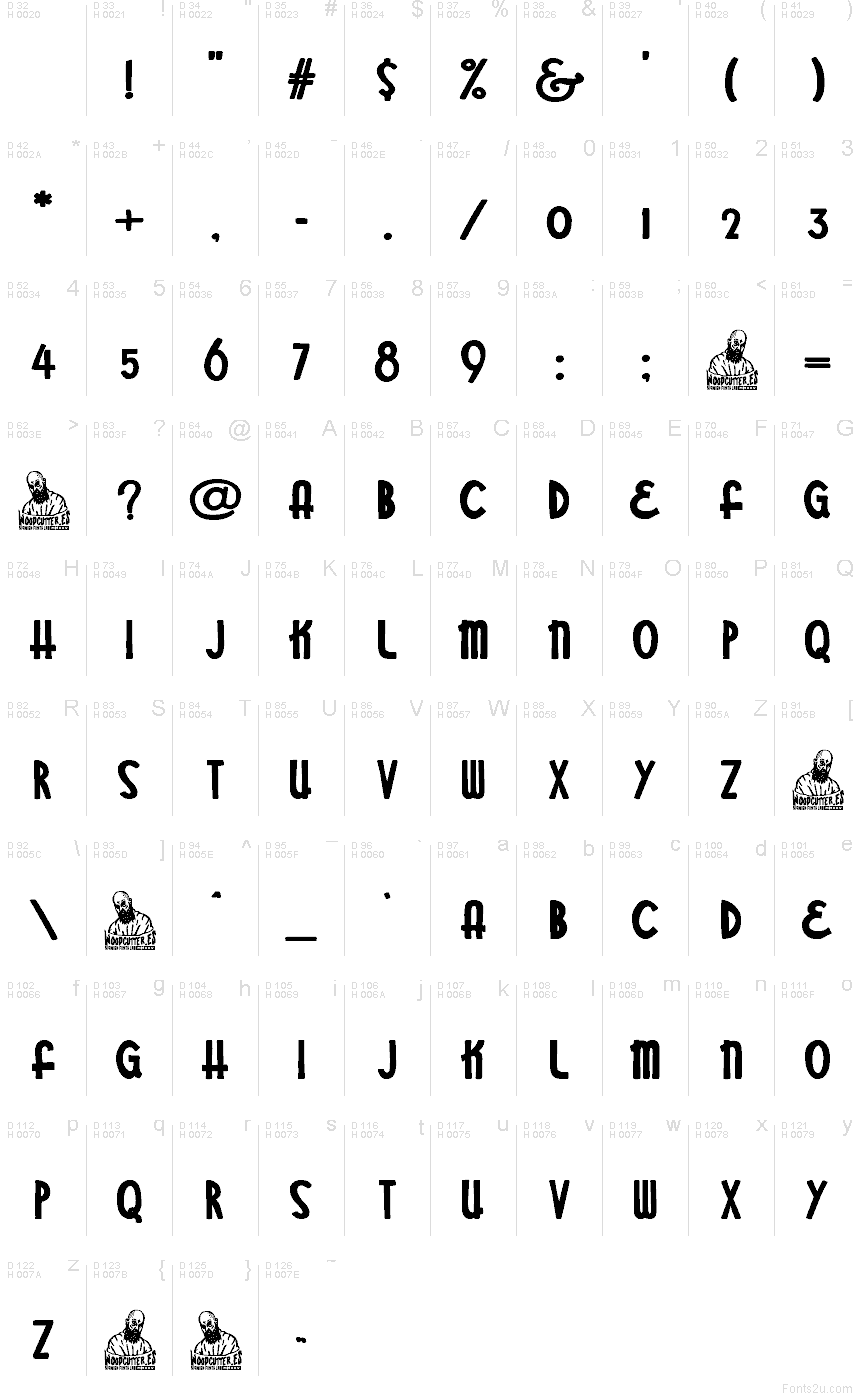
Chicago Boulevard
Chicago Boulevard de Woodcutter Manero es una tipografía gratuita de estilo Art Déco, pensada para titulares, que evoca los rótulos de los antiguos bulevares con la elegancia propia de los años 20. Sus formas son estrechas y teatrales, combinando curvas redondeadas con trazos transversales firmes y líneas verticales que imprimen un ritmo dinámico, casi como el de un cartel publicitario.
Encaja perfectamente en la identidad visual de coctelerías, marcas de moda, carteles de teatro, portadas de libros e invitaciones a eventos. También es ideal para títulos y líneas cortas donde su silueta alargada y erguida destaca por sí sola. Al ser una fuente gratuita, funciona mejor en aplicaciones breves de visualización, especialmente cuando buscas letras con un aire urbano, vintage y un toque cinematográfico.